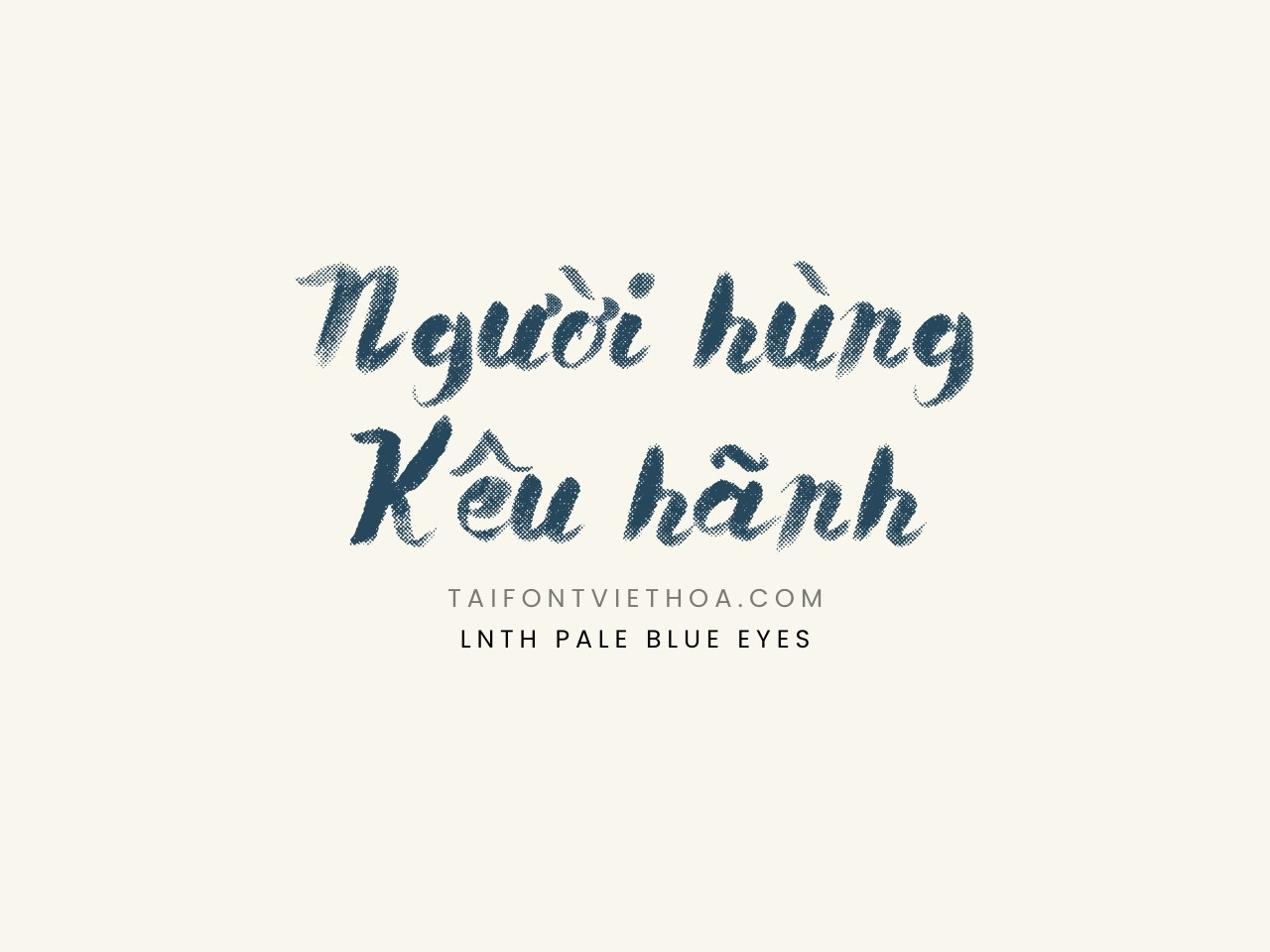
Font việt hóa LNTH Pale Blue Eyes
Giới thiệu về font LNTH Pale Blue Eyes – Lãng mạn, bay bổng và đầy cảm xúc
LNTH Pale Blue Eyes là font chữ viết tay mang phong cách mềm mại, được Việt hóa từ bản gốc thiết kế bởi Imagex – một tác giả nổi bật với các kiểu chữ cảm xúc và gần gũi. Font mang nét viết tay phóng khoáng, bay bổng và dịu dàng, như một bức thư tay chan chứa tình cảm. Phiên bản Việt hóa do Tuỳn Pucca thực hiện, hỗ trợ đầy đủ tiếng Việt và hơn 60 ngôn ngữ khác, giúp font trở thành lựa chọn lý tưởng cho các dự án thiết kế toàn cầu hóa nhưng vẫn giữ trọn nét cá nhân hóa.
Font đã được taifontviethoa.com sưu tầm, chọn lọc và kiểm duyệt kỹ lưỡng, ứng dụng thực tế trong các dự án thiệp chúc mừng, quà tặng cá nhân hóa, thiết kế poster lễ hội, banner truyền cảm hứng… Với vẻ ngoài dịu dàng, LNTH Pale Blue Eyes là chiếc cầu nối cảm xúc hoàn hảo trong thiết kế hiện đại.
Đặc điểm thiết kế và ứng dụng thực tế của LNTH Pale Blue Eyes
LNTH Pale Blue Eyes mang kiểu dáng handwritten mềm mại, các nét uốn lượn tự nhiên như viết bằng bút lông. Ký tự có độ cao chênh lệch, khoảng cách chặt chẽ tạo nên sự liền mạch. Font không quá cầu kỳ nhưng đầy cảm xúc, tạo ra phong thái lãng mạn, tinh tế và nghệ thuật. Đây là kiểu chữ tuyệt vời cho các dự án cần truyền đạt tình cảm hoặc phong cách nữ tính.
Ứng dụng lý tưởng của font bao gồm: thiệp Valentine, thiết kế sản phẩm dành cho phụ nữ, bao bì mỹ phẩm, bìa sổ tay, thiệp cưới, hoặc các ấn phẩm truyền cảm hứng trong ngành giáo dục – sáng tạo. Các ngành phù hợp: mỹ phẩm, giáo dục, ẩm thực, đồ thủ công, thời trang hoặc thương hiệu cá nhân hướng đến sự tinh tế và nghệ thuật.